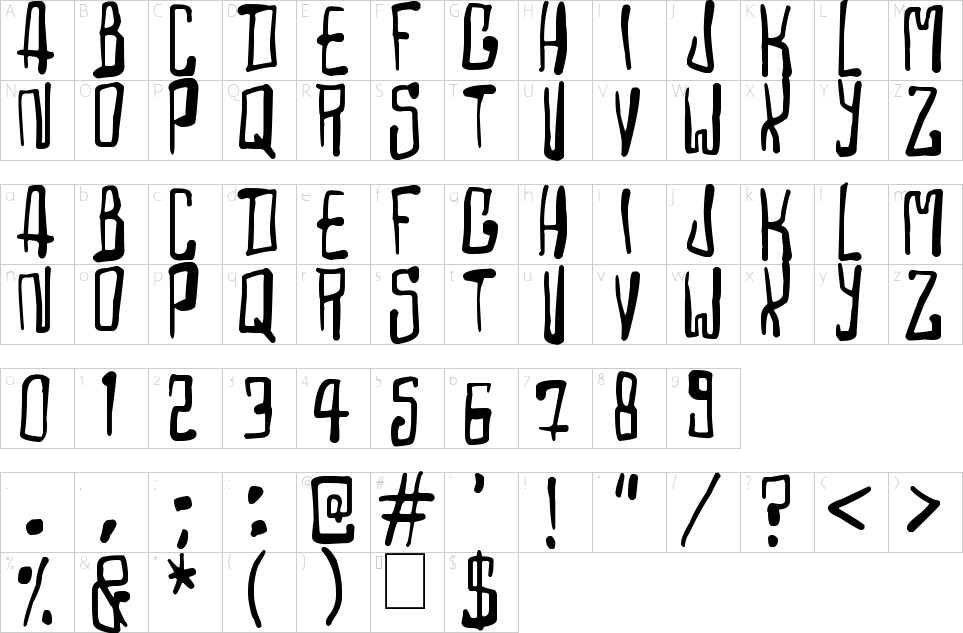
A fonte Madhouse é uma opção gratuita para designers e criadores de conteúdo em sua jornada criativa. Desenvolvida por Darrell Flood, Madhouse oferece uma combinação harmoniosa de linhas clean e textura, adequada para diversos tipos de design. Seja para criar logotipos, editoriais de moda ou qualquer tipo de layout digital, essa fonte irá dar o toque final com estilo. A Madhouse font foi descarregada 2,157 vezes, o que reforça sua popularidade como uma opção de fonte de qualidade para designers de gráficos. Download Madhouse aqui, e experimente como ela pode transformar seu trabalho.